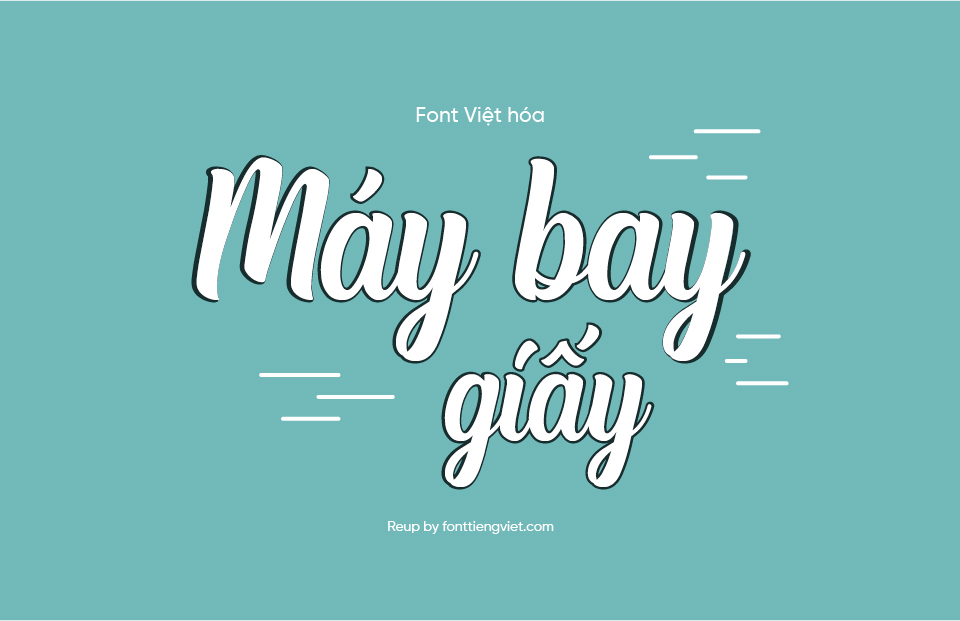
Khám Phá Vẻ Đẹp Độc Đáo Của Font Việt hóa MTD Chuck Noon Script
Font Chữ là yếu tố then chốt quyết định sự thành công của bất kỳ dự án thiết kế đồ họa nào, từ poster trường học cho đến các ấn phẩm cá nhân. Trong số vô vàn lựa chọn, Font Việt hóa MTD Chuck Noon Script đã nhanh chóng trở thành một cái tên được cộng đồng designer Việt Nam săn đón nồng nhiệt. Đây không chỉ là một phông chữ script thông thường mà còn là sự kết hợp hoàn hảo giữa nét vẽ phóng khoáng, hiện đại và khả năng hỗ trợ tiếng Việt cực kỳ mượt mà. Phông chữ này mang đến một luồng gió mới, đặc biệt phù hợp cho các dự án sáng tạo cần sự nhấn nhá mạnh mẽ, đầy cá tính.
Sự ra đời của phiên bản Việt hóa đã giải quyết triệt để vấn đề thiếu dấu tiếng Việt thường gặp ở các font nước ngoài, mở ra cánh cửa sáng tạo không giới hạn cho học sinh, sinh viên và các nhà thiết kế chuyên nghiệp. Chúng ta sẽ cùng nhau đi sâu vào khám phá chi tiết tại sao MTD Chuck Noon Script lại được yêu thích đến vậy và làm thế nào để khai thác tối đa tiềm năng của nó.
Sự Lôi Cuốn Khó Cưỡng Của Font Việt hóa MTD Chuck Noon Script
Điều làm nên sức hút đặc biệt của Font Việt hóa MTD Chuck Noon Script chính là phong cách viết tay (script font) đậm chất cọ vẽ (brush style). Mỗi ký tự đều được thiết kế với độ dày mỏng và độ nghiêng tự nhiên, mô phỏng chân thực cảm giác viết bằng bút lông hoặc cọ vẽ, tạo nên vẻ ngoài thô mộc nhưng không kém phần nghệ thuật. Đối với những dự án liên quan đến giáo dục, chẳng hạn như thiết kế bìa kỷ yếu, thiệp mời tốt nghiệp hay các ấn phẩm truyền thông của trường, phông chữ này giúp truyền tải thông điệp một cách ấn tượng và giàu cảm xúc hơn.
Các nhà thiết kế đã tinh chỉnh font chữ này để nó không chỉ đẹp trên màn hình mà còn hiệu quả khi in ấn, đảm bảo rằng mọi chi tiết, kể cả các nét nối nhỏ, đều rõ ràng và sắc nét. Điều này cực kỳ quan trọng đối với các ấn phẩm đòi hỏi chất lượng hình ảnh cao. Phong cách mạnh mẽ và năng động của MTD Chuck Noon Script cũng rất lý tưởng cho các poster quảng cáo sự kiện thể thao hoặc các hoạt động ngoại khóa sôi nổi của học sinh.
Đặc Điểm Kỹ Thuật và Tính Tương Thích Của Phiên Bản Việt Hóa
Phiên bản Việt hóa của font MTD Chuck Noon Script đã được xử lý vô cùng tỉ mỉ để hỗ trợ đầy đủ bộ ký tự tiếng Việt, bao gồm các dấu thanh, dấu mũ và các ký tự đặc biệt cần thiết cho việc gõ văn bản tiếng Việt chuẩn. Điều này giúp người dùng tiết kiệm thời gian đáng kể trong việc điều chỉnh thủ công các dấu bị lỗi hoặc bị lệch, một vấn đề phổ biến khi sử dụng các font không được Việt hóa hoàn chỉnh.
Sự linh hoạt trong thiết kế khiến MTD Chuck Noon Script trở thành lựa chọn hàng đầu cho nhiều mục đích sử dụng khác nhau. Đối với học sinh cấp ba đang chuẩn bị cho các dự án tốt nghiệp hoặc các cuộc thi sáng tạo, việc sử dụng một phông chữ độc đáo như thế này có thể giúp bài trình bày của họ nổi bật hơn hẳn. Nó mang lại cảm giác cá nhân hóa mạnh mẽ, thể hiện phong cách riêng biệt của người thiết kế. Nhiều chuyên gia SEO cũng khuyến nghị sử dụng các font chữ nổi bật và dễ đọc trong các hình ảnh minh họa bài viết nhằm tăng tính hấp dẫn và giảm tỷ lệ thoát trang.
Ngoài ra, font chữ này còn thường được kết hợp với các font chữ sans-serif đơn giản để tạo ra sự tương phản hài hòa. Chẳng hạn, MTD Chuck Noon Script dùng làm tiêu đề (headline) mạnh mẽ, trong khi nội dung chi tiết (body text) sử dụng một font sans-serif sạch sẽ như Roboto hoặc Open Sans. Sự kết hợp này không chỉ tăng tính thẩm mỹ mà còn cải thiện trải nghiệm đọc, đáp ứng tốt các tiêu chí của thiết kế hiện đại.
MTD Chuck Noon Script là một ví dụ điển hình về chất lượng của các sản phẩm Việt hóa hiện nay. Nó chứng minh rằng các nhà phát triển font Việt Nam đã đầu tư rất nhiều công sức để mang lại trải nghiệm tốt nhất cho người dùng trong nước, biến những phông chữ quốc tế trở nên hoàn toàn phù hợp với ngôn ngữ mẹ đẻ của chúng ta. Đây là một bước tiến quan trọng trong lĩnh vực chữ nghệ thuật và thiết kế tại Việt Nam.
Tóm lại, Font Chữ MTD Chuck Noon Script không chỉ là một công cụ thiết kế, mà còn là nguồn cảm hứng bất tận cho sự sáng tạo. Với khả năng Việt hóa hoàn hảo, phong cách script độc đáo và tính ứng dụng rộng rãi, nó xứng đáng có mặt trong thư viện của mọi designer. Nếu bạn đang tìm kiếm một phông chữ mạnh mẽ, ấn tượng để làm nổi bật các dự án học tập, các ấn phẩm kỷ yếu hay bất cứ sản phẩm truyền thông nào, thì Font Việt hóa MTD Chuck Noon Script chắc chắn là lựa chọn không thể bỏ qua. Hãy tận dụng tối đa vẻ đẹp của phông chữ này để nâng tầm chất lượng thiết kế của bạn ngay hôm nay!